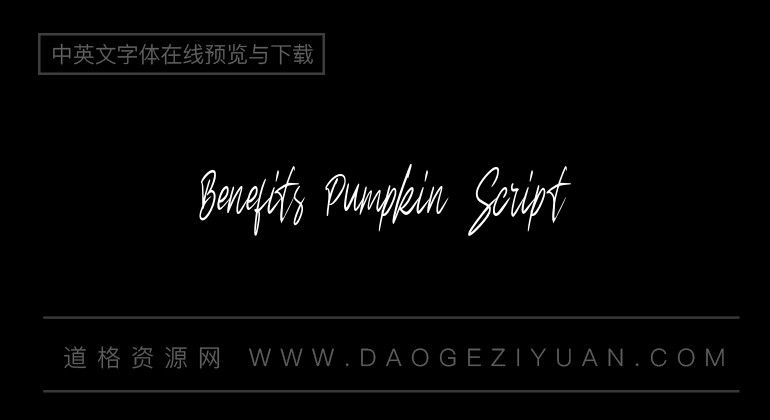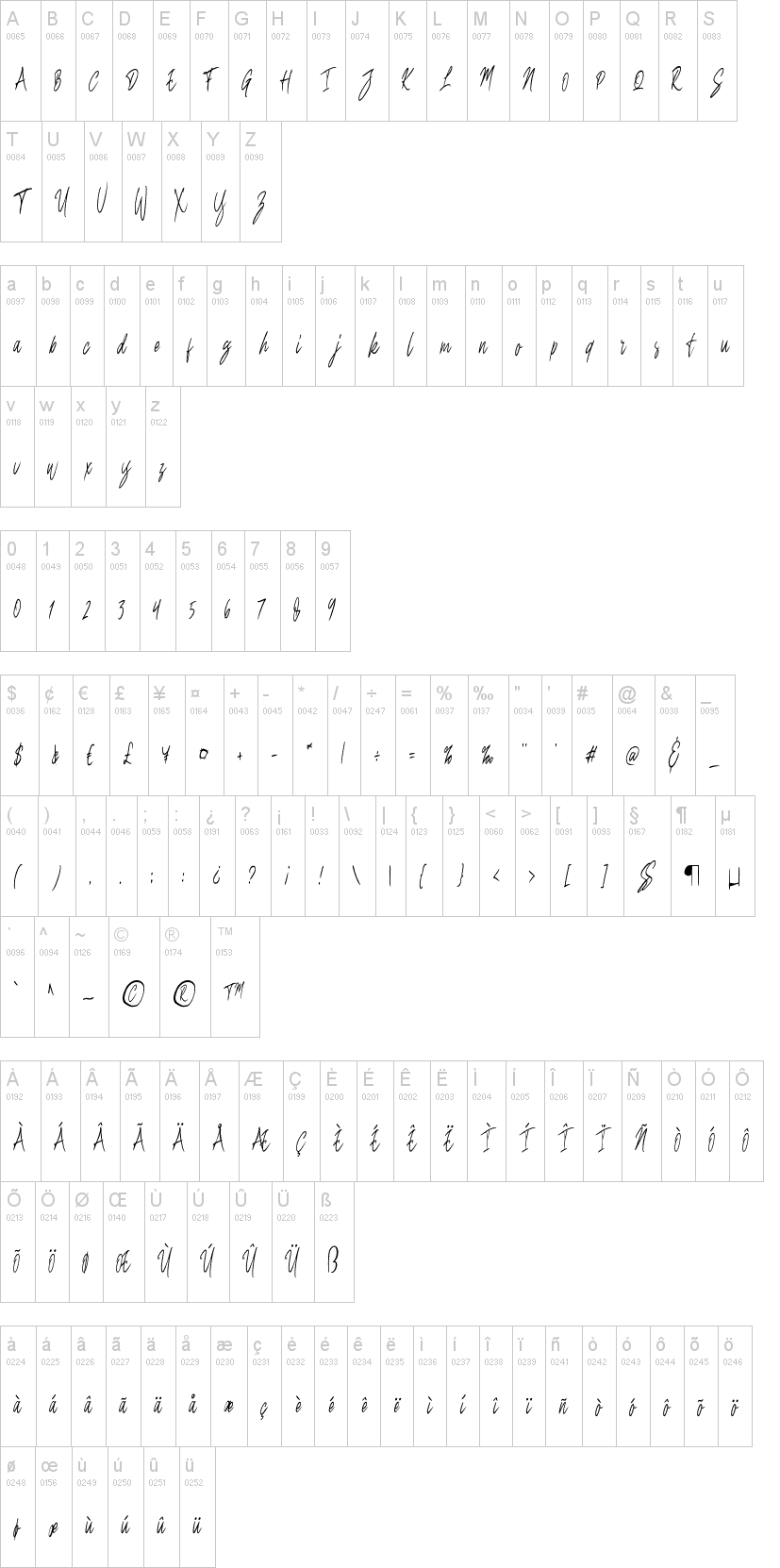
Benefits Pumpkin Script
Benefits Pumpkin Script 是一款由荷兰设计师Rene Bieder创作的手写体字体。它的特点是具有活泼的线条,每个字母都充满活力,仿佛是一位优秀的书法家自己手写的。它的字体特点是拥有清晰的细节,每个字母都有自己的特色,而且它的设计风格也很独特,比较适合用于创意的文字设计。
Benefits Pumpkin Script是一款非常不错的手写艺术字体,具有很好的视觉感,适合于文化类的宣传设计、商业类品牌的广告和产品包装设计以及个性化文字排版等较多场景。
Benefits Pumpkin Script字符映射图